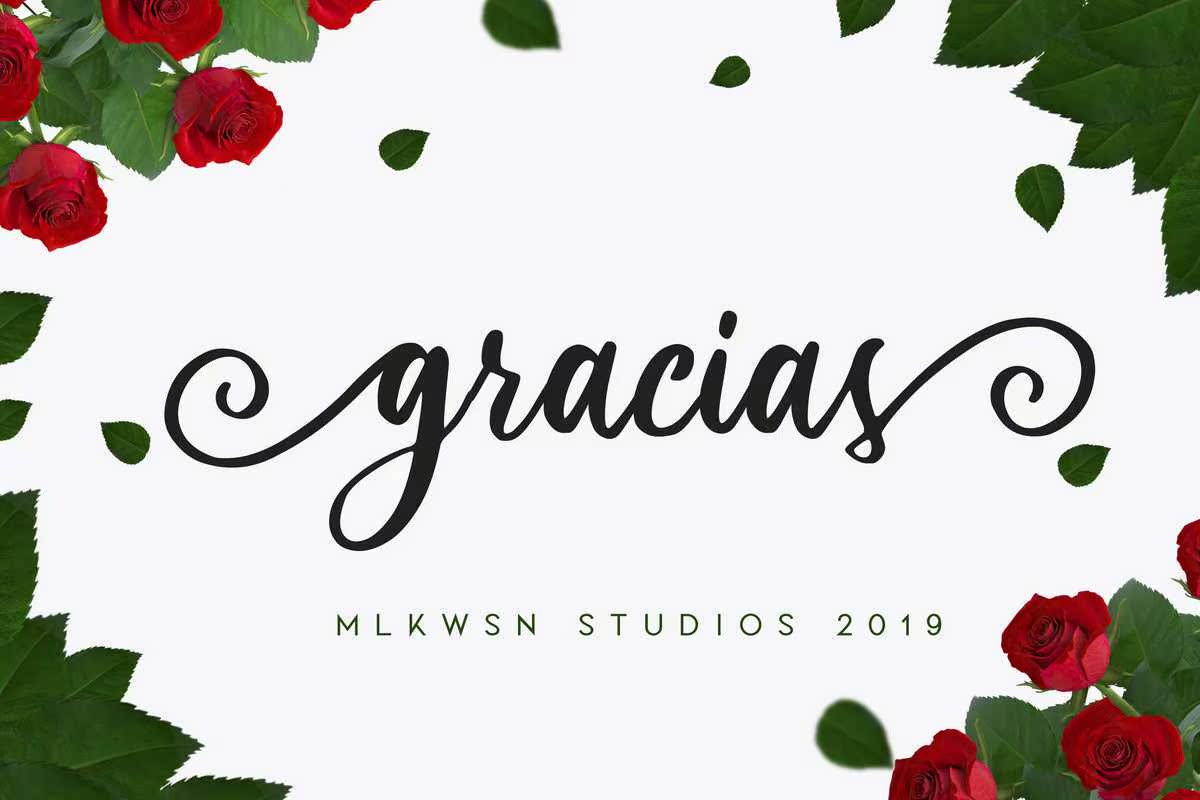
简介:这款由可爱和美丽的品牌材料激发灵感的美丽Pulscript Font让这款Font在您最近的项目中看起来更现代、更迷人。该路线适用于徽标和品牌、摄影、邀请、水印、广告、产品设计、文具、婚礼设计、标签、产品包装、,特殊物品或任何需要特殊品味的物品。简介使用受可爱和美丽品牌材料启发的美丽的Pulscript Font,可使此Font在您最近的项目中看起来更现代、更迷人。路线适用于徽标和品牌、摄影、邀请、水印、广告、产品设计、文具、婚礼设计、标签、产品包装、,特殊物品或任何需要特殊品味的物品。